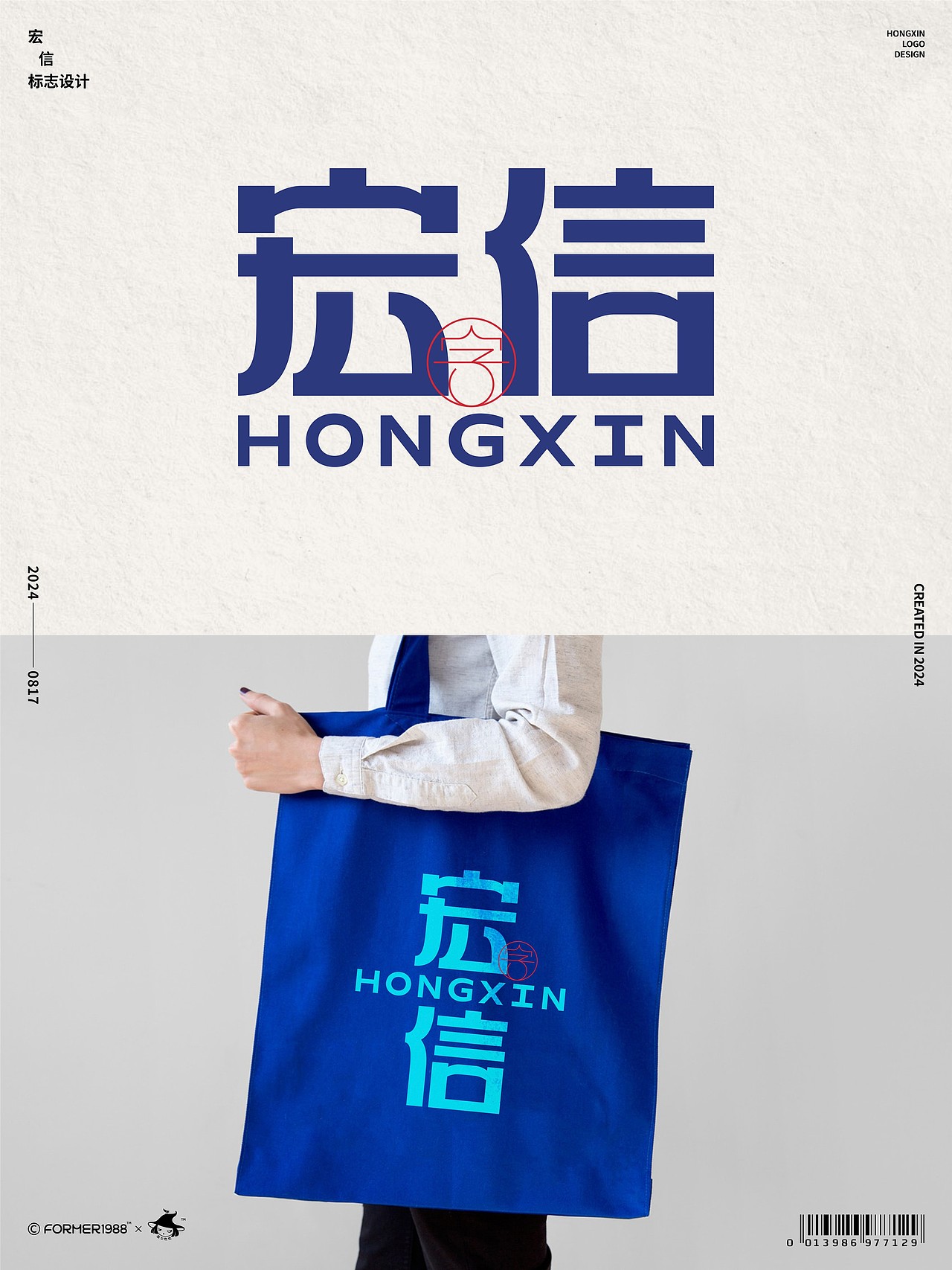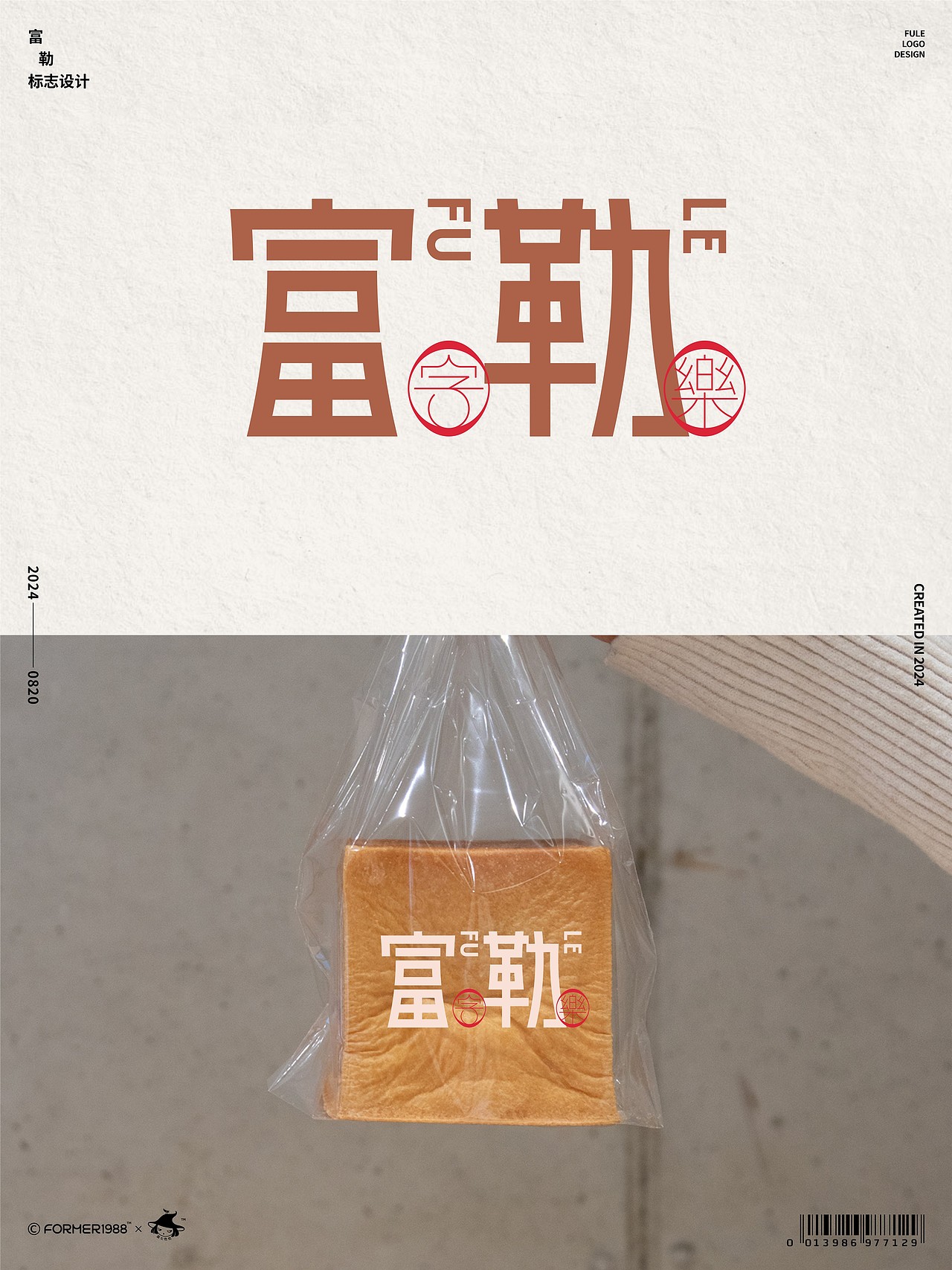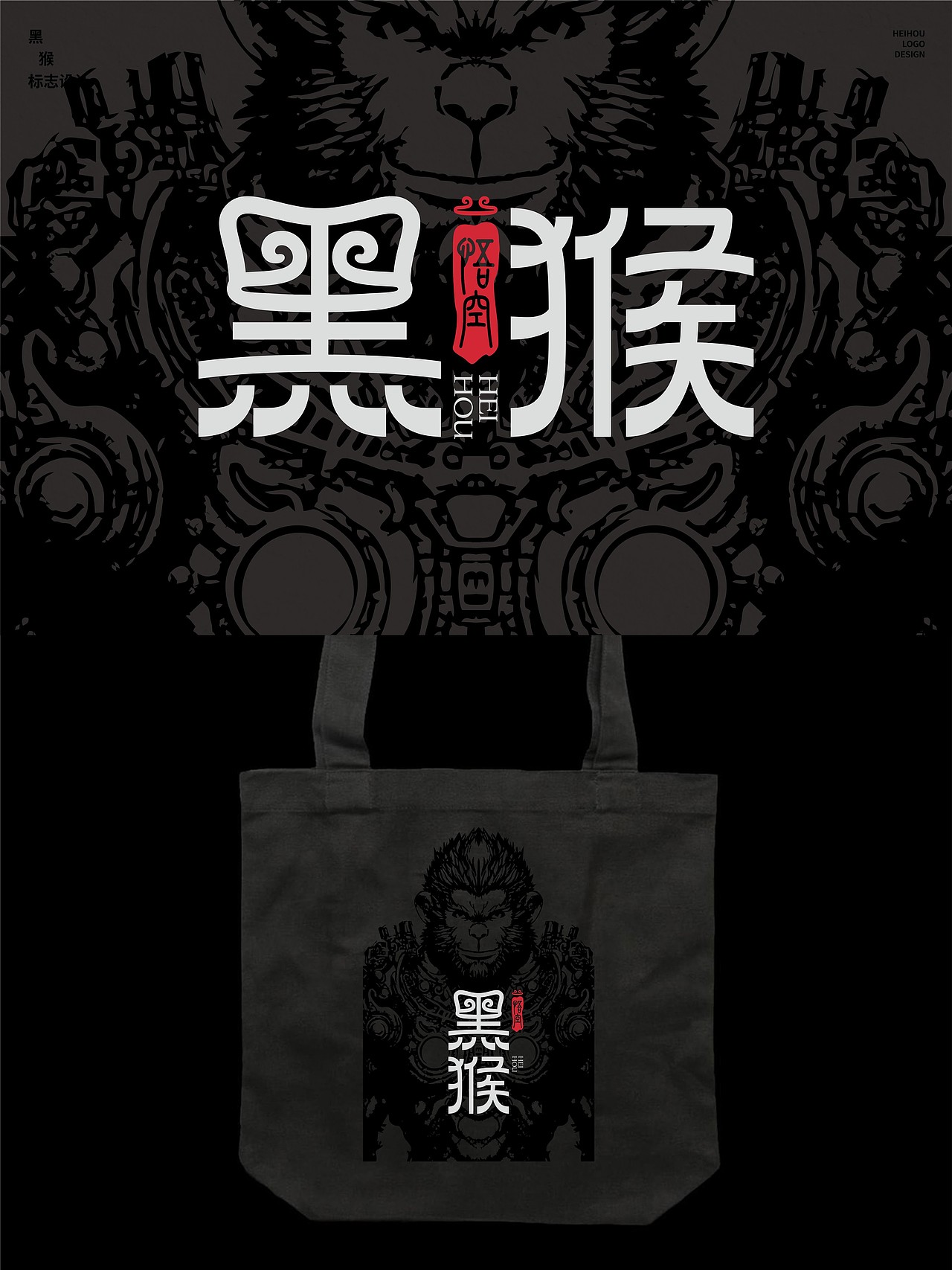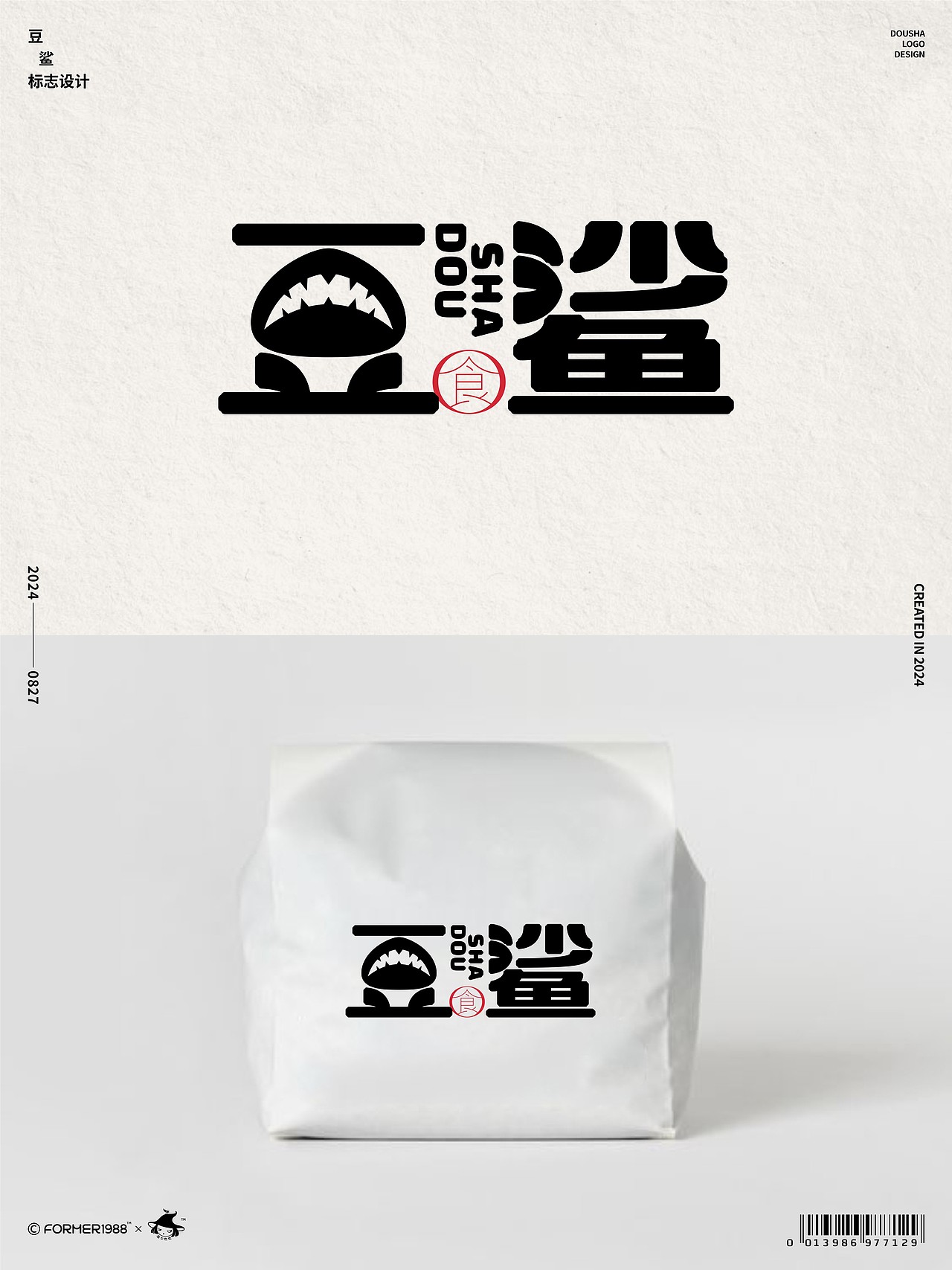
2024年8月下旬字体logo设计作品集
怎样设计一个中文字体logo
中文字体Logo在设计过程中,保持简洁和识别度是关键。一个成功的中文字体Logo能够传达品牌的核心价值,同时在视觉上具有强烈的冲击力和记忆点。
1. 确定风格与定位
品牌定位:首先要明确品牌的定位和目标受众。不同的品牌定位需要不同风格的字体设计,比如科技品牌通常使用现代感强的字体,而传统品牌可能更适合笔触厚重、古典风格的字体。
风格选择:根据品牌定位选择合适的字体风格,可以是简洁现代、传统古典、手写风、复古风等。
2. 字体选择与设计
现有字体修改:可以选择合适的中文字体进行修改和优化,加入品牌元素,使其独特化。
原创设计:从零开始设计独特的字体,这样能够完全符合品牌需求,同时避免版权问题。原创字体需要考虑笔画的粗细、间距、比例和结构。
3. 结合品牌元素
图形结合:可以将品牌的图形元素(如标志、吉祥物、图案)与字体巧妙结合,增强识别度。
颜色应用:选择合适的品牌颜色,并应用于字体设计中。颜色能传达情感和品牌个性。
4. 结构与排版
整体构图:确保字体的排版整齐,结构紧凑,不同字之间的间距均匀。
形态与对称:字体形态要和谐统一,避免过于复杂的设计导致识别困难。
5. 测试与优化
可读性测试:确保Logo在不同尺寸和背景下的可读性。Logo需具备良好的缩放性能,保证在小尺寸和远距离也能清晰辨认。
受众反馈:收集目标受众的反馈,根据意见进行微调和优化。